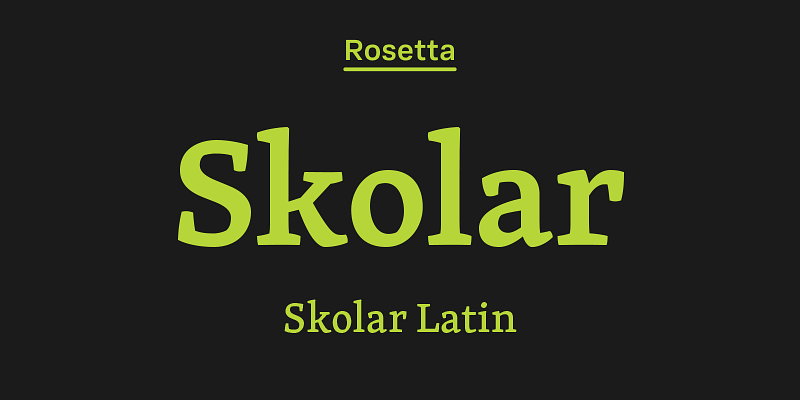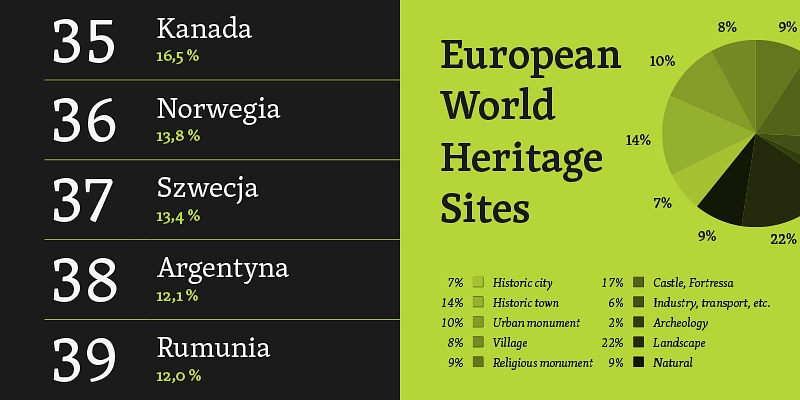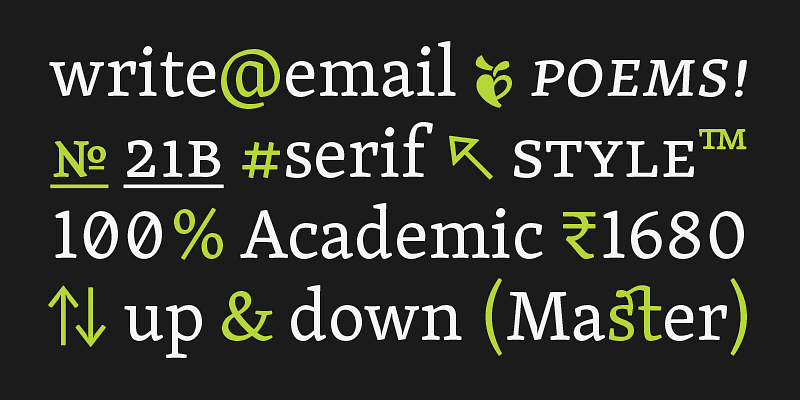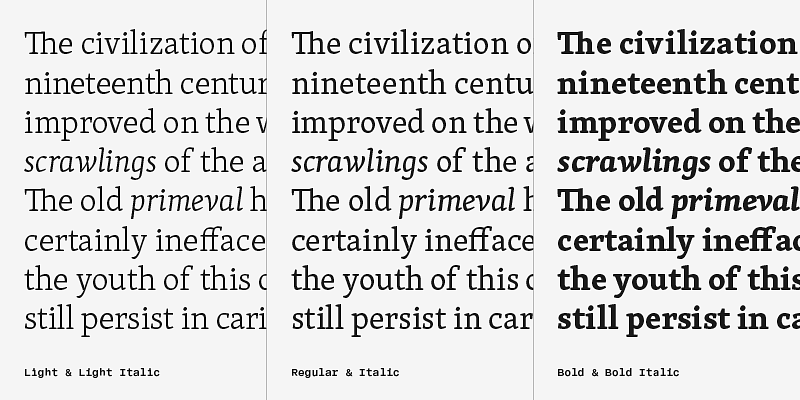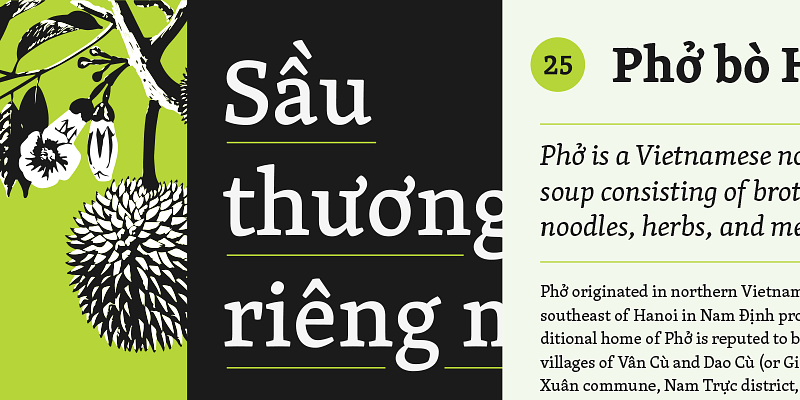
Skolar es un tipo de letra de texto robusta diseñado para abordar las necesidades de una tipografía seria. Un clásico en la web, se ha utilizado ampliamente en diversas plataformas y con diferentes fines.